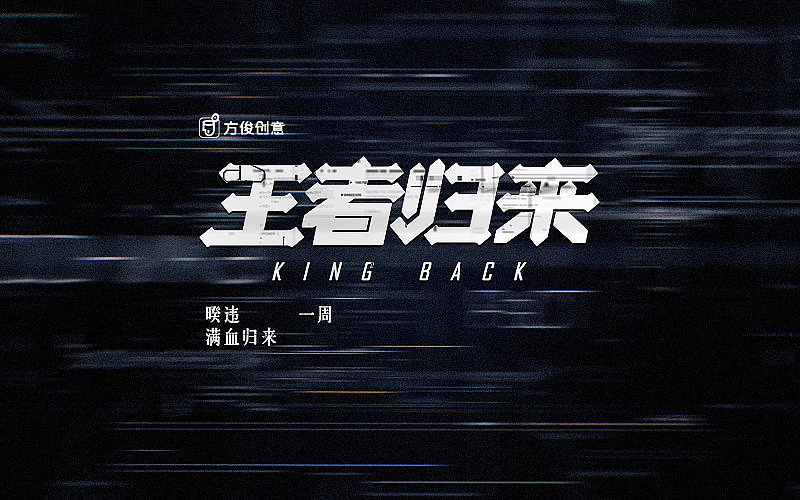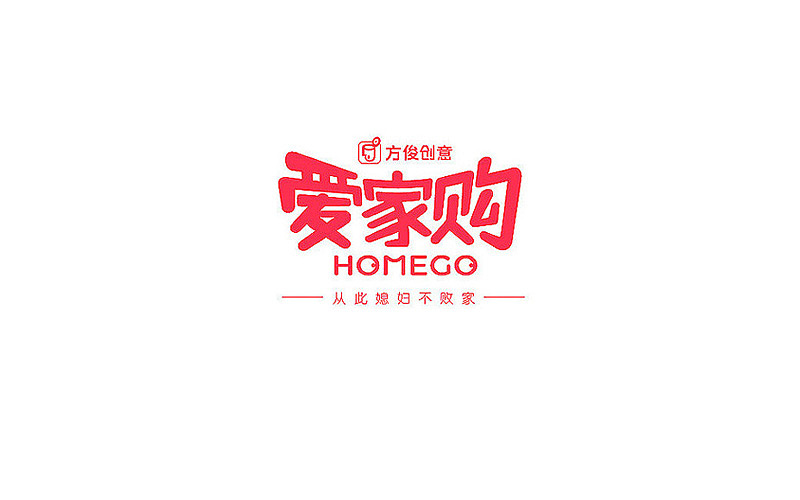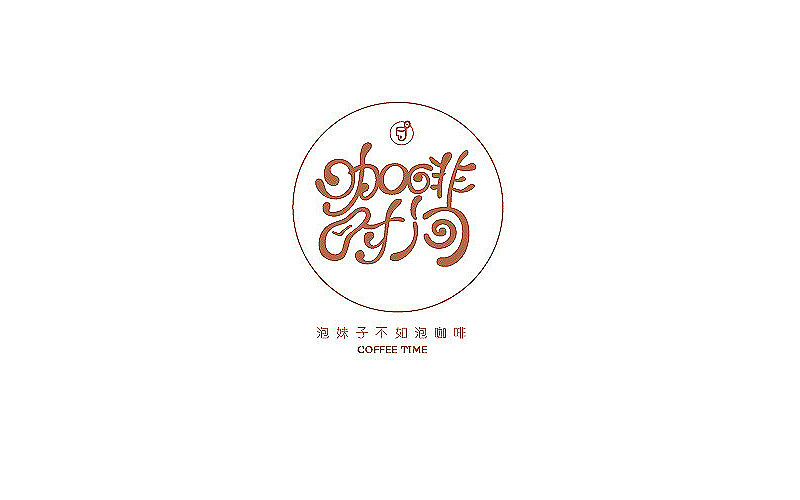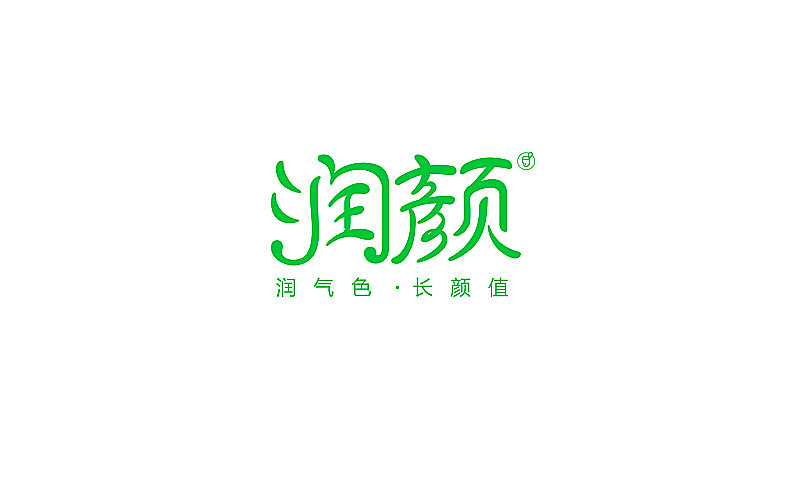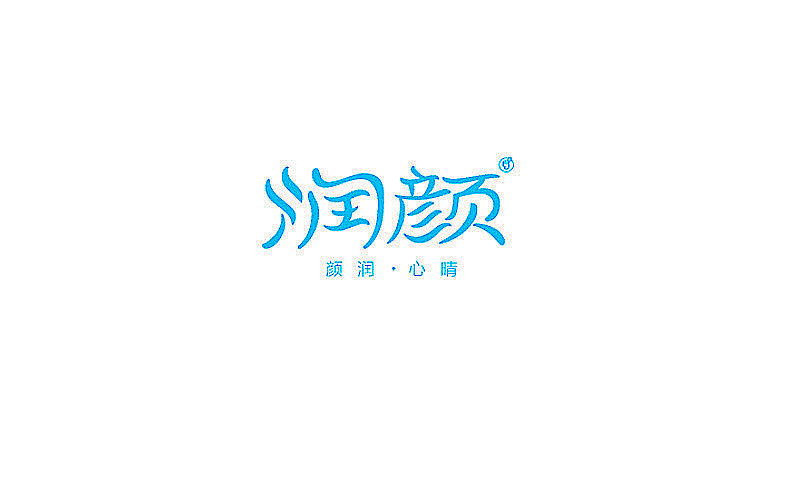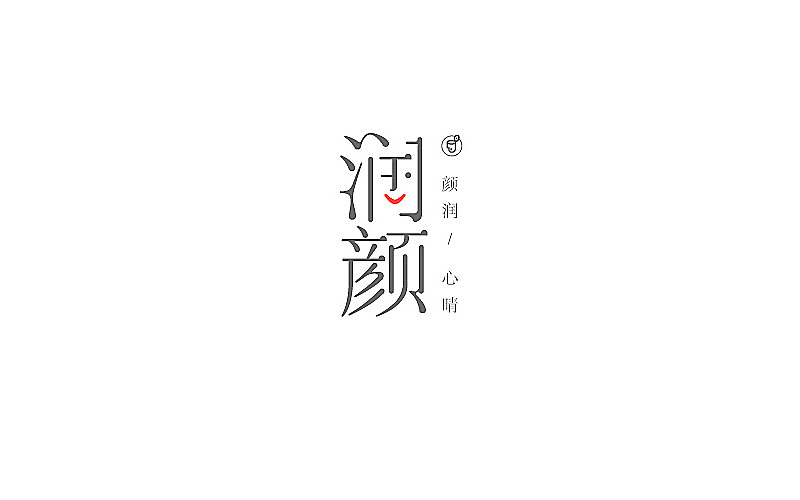
反正有~咖啡时光
去年偶然加入字体帮,开始和很多字体设计师做命题字体,和大家一样,我从几期被推到封面的经历里找到了愉悦感(~屌丝一枚,人穷志短),于是一有时间就扎到字体里,沉迷学习无法自拔……
2017年,貌似自嗨的字体命题已经没办法满足大伙强烈的生理需求,机智的兵哥@刘兵克,果断提升命题难度系数,将矛头对准商业品牌。无疑戳到了很多设计师的痛,但痛并快乐,快乐着。相信通过一次一次的商业字体练习,我们可以很大程度地提升平日工作的效率,做更好的商业作品出来!
愉快的周末,年味未淡,元宵正浓,趁时光正好,那就开始新年第一波字体汇总吧~
既然是虚拟品牌,尺度大一点,应该不过分~
就是能坚持一直做一件事的人,就是王者!很想弄出信号干扰的效果,不知道有什么特别的方法~
一个水果店名,不想按套路出牌,谁说水果店一定就是软软的,飘逸的感觉,个性大于属性的时代,平庸离失败不远~ 小朋友,不好好读书,长大就送你去种田,种乐果~!
一家以家居产品为主的中高端购物网站,嗯~媳妇爱上了它,以后不会乱败家~
一个人的咖啡厅,一不小心和孤独撞个正好!
时光荏苒,光阴如梭,泡妹子不如泡咖啡~!
来啊,坐坐啊,反正有,大把咖啡时光~(其实是开始把命题弄错了,时间变成了时光)
给央视益智节目做的更新,按照对栏目的理解,融合一些对新春开年大吉的元素,大尺度的进行了颠覆。有趣就要真有趣~!
欢迎进入25小时便利店,颠覆您的世界观!仔细看,我把脸蛋藏在字体之间了~囧
颜是表象,润才揭示内心的淡定从容~ 做一个润万物的人吧!
别以为长得好看就了不起,不过你长得还真的真的蛮好看耶。
润粗好气色,润粗高颜值~!干了这碗毒鸡汤!
颜值高到鲜衣怒马心情一片大好
独特的形式,由内而外的润颜~
一本正经地不正经